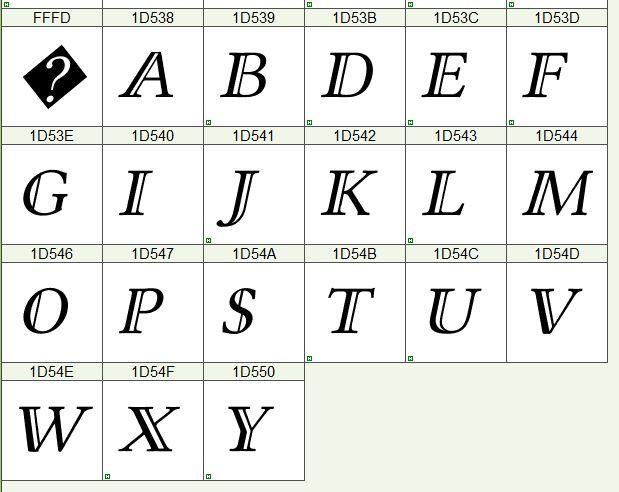
Schriftart für Wertemengen (vertikaler Strich)
ich suche eine passende Schriftart für mathematische Wertemengen.
Die Darstellung von Wertemengen wird idR durch doppelte schräge Striche dargstellt, das aber falsch ist.
Gesucht wäre folgende Darstellung "|N".
Man kann Latex verwenden. Ist aber hier nicht relevant.
Kennt jemand eine passende Schriftart?
Meinst du solche ähnlichen Buchstaben?
Diese findest du ganz am Ende der Zeichentabelle in den Linux Libertine-Schriften - ich hatte hier zufällig einen kursiven Schnitt im Font-Editor geöffnet, un dieses Bild zu machen in den normalen und fetten Schnitten sind dann auch die geraden Formen der Mengen-Buchstaben enthalten, wie sie in Unicode definiert sind.
Meinst du solche ähnlichen Buchstaben?
Oder vielleicht einfach Schriften mit senkrechtem Strich (der mit nachfolgenden Buchstaben harmoniert)? :-?
Falls letzteres, gibt es schier endlos viele Schriften, denn | ist in fast allen Schriften enthalten. Um nach Schriften zu suchen, siehe z.B.
Die Darstellung von Wertemengen wird idR durch doppelte schräge Striche dargstellt, das aber falsch ist. Gesucht wäre folgende Darstellung "|N".
Ich habe bisher weder doppelte schräge Striche noch |N als Darstellung für Wertemengen gesehen. Was genau meinst du?
Ich glaube schon, das "brokenpipe" sehr wohl diese "Mathematical Double Struck Capital ... " Zeichen aus dem Unicode-Bereich 1D538 bis 1D550 meint, denn ich erinnere mich noch genau, was der Professor in meinem Maschinenbau.Studium an die Tafel kritzelte, als ich Mengenlehre büffeln musste. Seltsam nur, das hier die Definition der Doppelstrich-Buchstaben so lückenhaft ist, und ausgerechnet kein N dabei ist.
Steht das N nicht für natürliche Zahlen? Wikipedia meint dazu, dass der Schrägstrich doppelt dargestellt wird. Aber ich kenne es von der Tafel auch nur mit zwei senkrechten Strichen links (analog R, Q und C, nur bei Z habe ich den doppelten Schrägstrich schonmal in Kreide gesehen).
Die Menge der natürlichen Zahlen wird nach Wikipedia mit ℕ (U+2115) abgekürzt. Und bei diesem N ist eben der Schrägstrich gedoppelt. Dieses Symbol wird auch im Stöcker-Taschenbuch (Harri Deutsch 1993) verwendet.
In anderen Büchern (Mathematik Sekundarstufe II, Cornelsen 1987 oder Papula: Mathematik für Ingenieure, Vieweg 1991) wird die vom Fragesteller gesuchte Form verwendet, wo eben der linke senkrechte Strich des N gedoppelt wird.
Ob beide Arten mal gleichberechtigt nebeneinanderstanden oder ein Wandel von |N zu ℕ stattfand, kann ich leider nicht sagen.
Die Menge der natürlichen Zahlen wird nach Wikipedia mit ℕ (U+2115) abgekürzt.
Das beantwortet diese Frage:
Ich glaube schon, das "brokenpipe" sehr wohl diese "Mathematical Double Struck Capital ... " Zeichen aus dem Unicode-Bereich 1D538 bis 1D550 meint, denn ich erinnere mich noch genau, was der Professor in meinem Maschinenbau.Studium an die Tafel kritzelte, als ich Mengenlehre büffeln musste. Seltsam nur, das hier die Definition der Doppelstrich-Buchstaben so lückenhaft ist, und ausgerechnet kein N dabei ist.
Weil das eben schon in der BMP codiert ist.
Und hier ein paar freie Schriften mit ℕ. Interessanterweise ist in Linux-Libertine/Biolinum-Superfamilie der linke Balken verdoppelt:
Die Liste mathematischer Symbole führt auch nur das Zeichen 9b3ecd4f5f0cc174717f19cec0743fcd.png für die natürlichen Zahlen auf.
Sind beide „ℕ“-Varianten dann so zu sehen wie beispielsweise die beiden Formen (offen/geschlossen) für „a“?
Vielen Dank für eure zahlreichen Antworten und Hilfestellungen! Die Linux Libertine Schriften machen schon einen sehr guten Eindruck. Leider fehlt genau das N.
Um ein bisschen konkreter zu werden, hier sind die korrekten Darstellungsformen von mathematischen Mengen:
Der Autor stellt auch eine Schriftart zur Verfügung. Es fehlt jedoch zum einen die Wertemenge, zum anderen schaut sie nicht extrem toll aus.
Nein, das N und andere vfehlt nicht in der Libertine/Biolinum-Familie, sondern steht, Unicode sei Dank - weiter in der Mitte der Schriftcodierung.
Offensichtlich hat Unicode unter den Buchstabenähnlichen Zeichen zunächst nur die wirklich wichtigen C, H, N. P, Q, R und Z zwischen u+2102 und u+2124 ziemlich kunterbunt aufgenommen, und dann gaaaaanz weit hinten an u+1D538 dann die restlichen Buchstaben nachgeliefert. Die ersten Unicode-Indexes sollten noch in deutlich mehr Schriften enthalten sein, die über UTF8 hinausagehendebn dagegen sind wohl nur selten anzutreffen.
Dass nur diese genutzt wird (meiner Tochter wird in der 5 Klasse Gymnasium auch diese Schreibweise beigebracht) heißt aber nicht zwangsläufig, dass nur diese zulässig wäre.
Das wollte ich damit auch nicht ausdrücken. Es scheint nur irgendwann eine Vereinbarung (Empfehlung?) gegeben zu haben, im schulischen Kontext nur diese Variante zu nutzen.
Vielleicht findet sich noch ein offizielles Dokument...